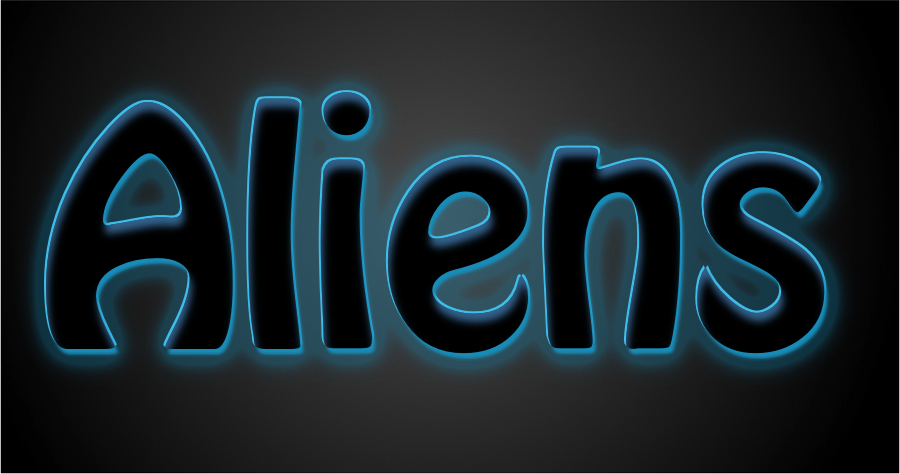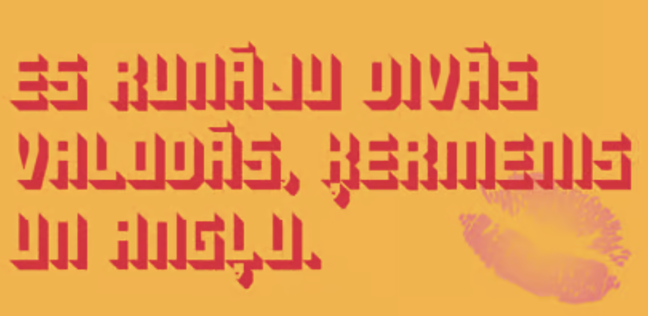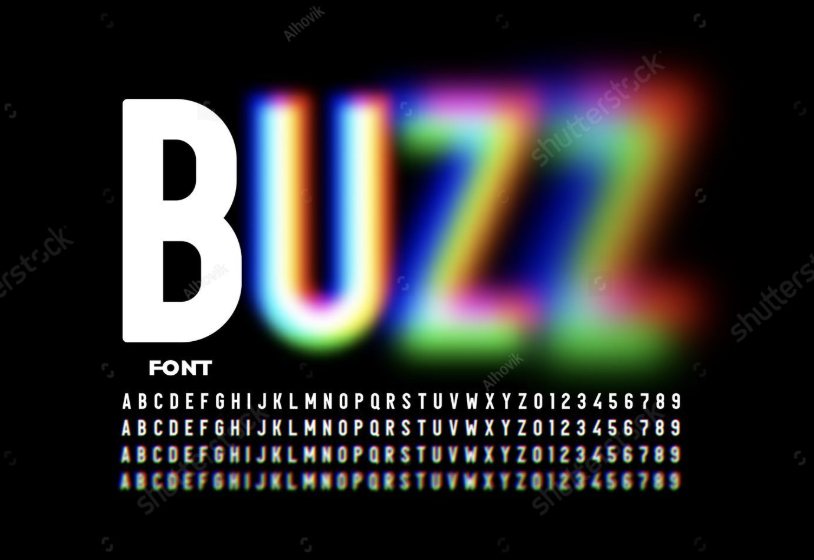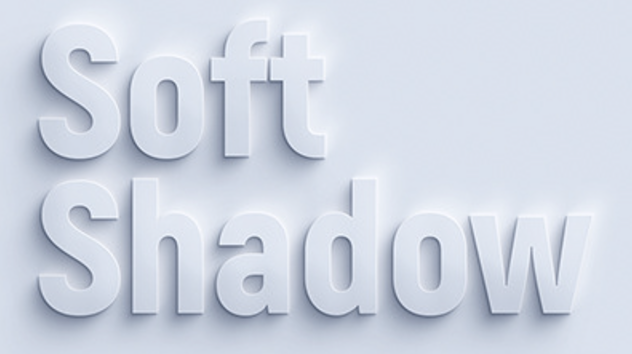
Vytvořte tučný a působivý text s efekty stínového písma
Chcete, aby váš text vynikl efekty stínového písma? Najděte nejlepších 6 nástrojů, které přidají stínové efekty do vašeho textu pro odvážné, profesionální návrhy, které zanechávají trvalý dojem.
Efekty stínového písma jsou ideální pro navrhování podmanivých titulků na plakátech, dynamických příspěvcích na sociálních médiích a nápadných bannerech webových stránek. Dodávají hloubku a rozměr, takže váš text vyniká a zachycuje pozornost. Tato technika je nezbytná pro projekty, kde je prioritou odvážná a působivá typografie.
V tomto článku se dozvíte, jak vytvořit efekty stínového písma a najít několik webových stránek, které obsahují možnosti připraveného designu. Ať už jste začátečník nebo zkušený designér, tyto tipy a zdroje zvýší vaši typografii a učiní vaše projekty skutečně nezapomenutelnými.
Různé typy stínových písem
Písma se stínovým efektem jsou všestranným nástrojem pro přidání hloubky a kreativity do textových návrhů. Každý typ nabízí jedinečné efekty, které vám umožní přizpůsobit typografii konkrétním potřebám. Zde je deset typů stínových písem a jejich použití.
1. Zahodit stínové písmo
Drop stín písma vytvořit stín mírně pod a offset od textu. Tento efekt přidává hloubku a pomáhá textu vyniknout, takže je široce používán v titulcích a loga.
2. Písmo stínů vnějšího světla
Vnější světelné stíny obklopují text jemným, zářícím efektem. Tento styl funguje dobře na tmavém pozadí a je ideální pro upoutání pozornosti na text jemným, ale pozoruhodným způsobem.
3. Vnitřní stínové písmo
Vnitřní stíny jsou umístěny uvnitř textu a vytvářejí zapuštěný nebo rytý vzhled. Tento efekt se často používá v elegantních nebo sofistikovaných návrzích, které nabízejí jedinečnou vizuální přitažlivost.
4. Rozmazané stínové písmo
Rozmazané stíny jsou měkké a nedefinované, což dává textu mlhavý nebo zasněný vzhled. Tento styl funguje nejlépe pro přidání jemného a uvolněného doteku do návrhů.
5. Vícenásobné stínové písmo
Tento typ zahrnuje více překrývajících se nebo rozložených stínů, které vytvářejí dynamický, vrstvený efekt. Je oblíbený v moderních, uměleckých a experimentálních typografických návrzích.
6. Neonové stínové písmo
Neonové stínové písma napodobují záři neonových světel a vytvářejí živý a elektrizující text. Tento styl je ideální pro odvážné, poutavé titulky a návrhy.
7. 3D stínové písmo
3D stínová písma dávají textu trojrozměrný efekt, takže vypadá vyvýšený nebo vyřezávaný. Jsou běžně používány v logech, titulech a reklamách pro dramatický vzhled.
8. Měkké stínové písmo
Měkké stíny postupně slábnou a vytvářejí jemný důraz na text. Tento efekt je vhodný pro minimalistické a jemné návrhy, kde je potřeba lehčí dotek.
9. Písmo tvrdého stínu
Tvrdé stíny jsou ostré a definované, nabízejí odvážný a nápadný vzhled. Používají se k vytváření působivých vizuálů a silných kontrastů.
10. Barevné stínové písmo
Barevné stínové písmo používá odstíny mimo šedou nebo černou, což dodává textu živost a kreativitu. Jsou ideální pro hravé a poutavé návrhy.
Překlad: Editor videa pro desktop CapCut je jedním z nejlepších nástrojů pro aplikaci stínového textu na vaše video.
CapCut desktop video editor usnadňuje přidání stínových efektů do textu, aby byl výraznější. Naštěstí nástroj poskytuje možnost upravit polohu stínu, rozostření a dokonce i jeho úroveň neprůhlednosti, aby se dokonale vešly do videa. Kromě stínového textu má editor videa CapCut mnoho dalších silných funkcí pro úpravy. Můžete vybrat řadu stylů písma, upravit velikost textu, přidat samolepky, odstranit blikání , a použít filtry a efekty. Tyto funkce, aby to vynikající volbou pro vytváření professional-quality videa s dynamickým textem a vizuály.
Klíčové vlastnosti
• Různé stínové efekty
CapCut vám umožní Přidat text do videa a stínové efekty na text pro zdůraznění v tutoriálech nebo intros. Můžete nastavit neprůhlednost, pozici a rozostření pro vlastní vzhled.
1. Jak může stín stylu písma ovlivnit můj text?
Přidání stínu do textu vytváří kontrast a zvyšuje viditelnost, což činí váš obsah poutavějším. Zdůrazňuje klíčové informace a upozorňuje na důležité zprávy. Pomocí nástrojů pro úpravu videa CapCut můžete použít stínová písma a ve videích a dalších kreativních projektech posunout svůj návrh textu na další úroveň.